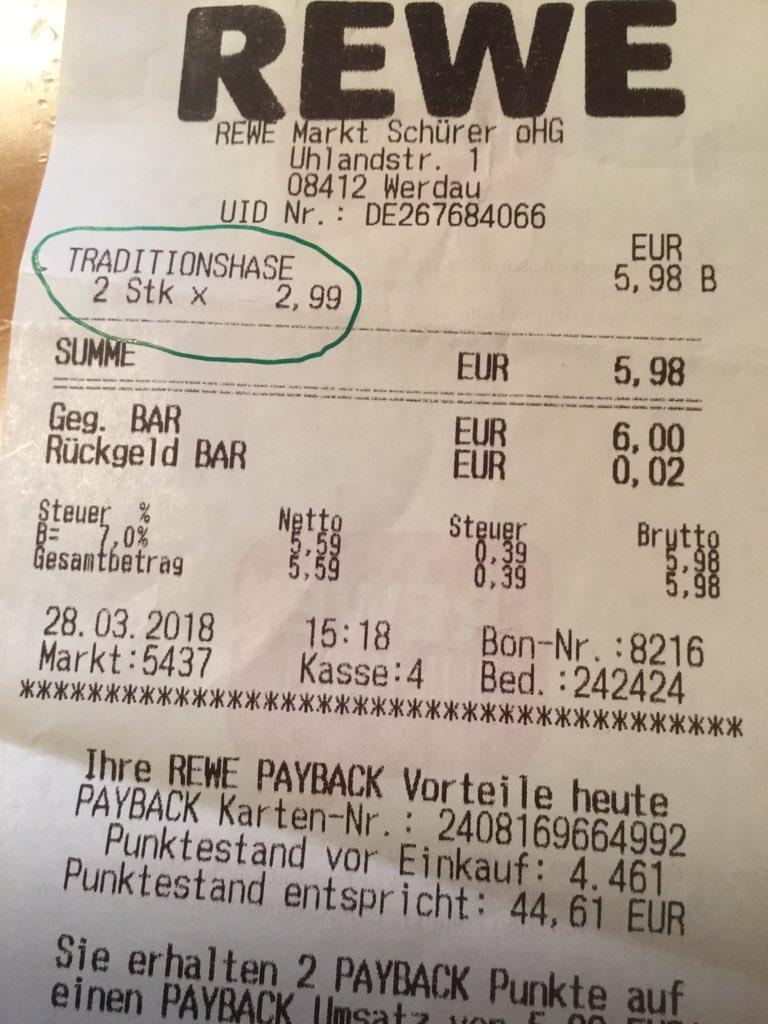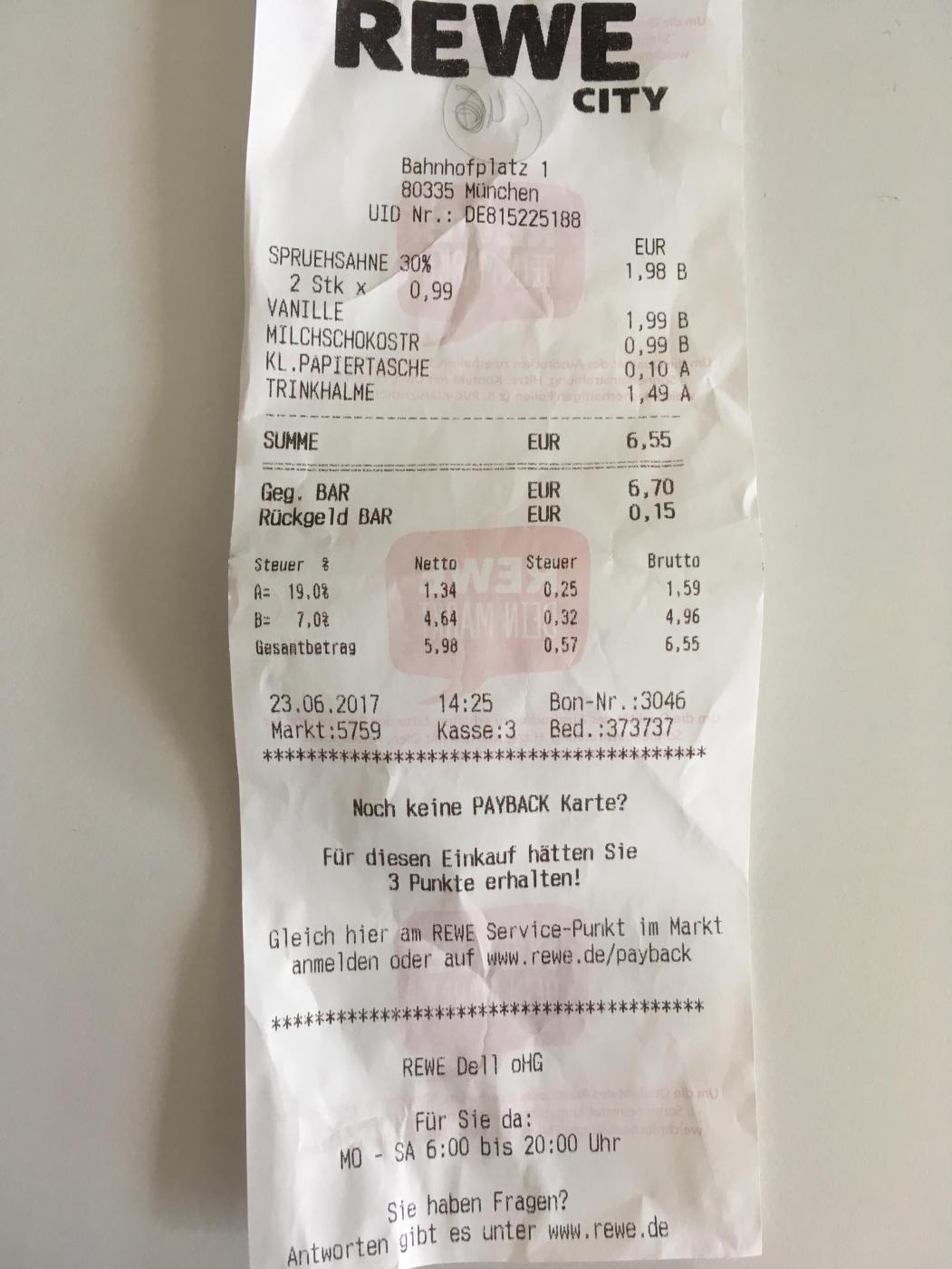
Rewe-Kassenbon-Schriftart
Ich bin auf der suche der Genuzten Schriftart der Rewe / Penny-Markt kassenbons.
Beide nutzen die selbe schrift art. Mit analyse programmen bin ich leider nicht sehr weit gekommen.
Wenn möglich suche ich eine Kostenlose alternative das die Orginale schriftart vermutlich nicht puplic ist , ist mir klar
eine alternative sollte so nah wie möglich an das orginal kommen.
Als kleiner extra hinweis es handelt sich nicht um eine Typische Pixelschrift diese wird bei Rewe seit jahren nicht mehr genuzt.
Das wurde hier schon diskutiert:
Ganz genau eben nicht , dort wird jedgliche art von kassen bons diskutiert da jede kette andere schriften nutzt und da keine einzige schriftart in diesem  über 1 Jahr alten Artikel nur annähernd dem orginal entspricht habe ich hier eine explizite frage nach REWE
Zusätzlich habe ich extra nochmal betont das ich keine pixel schriftart suche da dies seit über 1  jahrzehnt bei Kassenbons garnicht mehr genuzt wird
Die Schriftart hängt vom verwendeten Bondrucker ab. Da verschiedene Rewes verschiedene Kassensysteme verwenden, wäre eine Möglichkeit, auf dem Drucker nachzuschauen. Die Bezeichnung steht ja meist gut sichtbar drauf. Das führt dann über die Datenblätter zu den hardwaremäßig eingebauten Schriftarten.
Bei Epson-Druckern beispielsweise ist das "Schriftart A: 12 x 24" und "Schriftart B: 9 x 17", jeweils mit 2 Punkt-Zeichenabstand. Das Logo wird üblicherweise als bmp eingebunden, weil das keine Geschwindigkeitsnachteile beim Druck mit sich bringt.
Leider wieder falsch, das kassenstystem ist bundesweit bei allen Rewe märkten bei allen penny-märkten und bei allen Toom märkten gleich.
Es ist keine bondrucker schriftart, da Toom und Rewe zum beispiel verschiedene Drucker  nutzen die schriftart aber identisch ist.
Wie erklärst du dann, dass auf diesen zwei Rewe-Kassenbons unterschiedliche Schriftarten verwendet werden, wie man an den Zahlen leicht sehen kann?
Ah so. Das heißt, Rewe hat nach dem 23.6.17 bundesweit neue einheitliche Kassensysteme bekommen? Hab ich gar nicht mitbekommen …
Die alten Wincore Nixdorf TA 85 Kassensysteme werden seit anfag 2017 Bundesweit ausgetausch durch das neue Wincor-Nixdorf BA93 Touch  inklusive Kundenscanner für smartpones.
Wie du dir selbst anschauen kannst. Vereinzelt gibt es in deutschland private Märtke die bei der umstellung einspaarungen gemacht haben
wie zum beispiel , Altes kartenlesegerät ,oder alte drucker behalten. Dies ist aber sehr selten.
Und dann ist es auch bei den neuesten Kassensystemen nach wie vor eine Pixelschrift, bei den die Glyphen sogar, anders als bei alten PC-Pixelschriften sogar zeilenweise statt spaltenweise codiert. Der Drucker besteht nämlich aus einer Heizelement-Zeile, die über die Breite des Thermopapier-Streifens reicht, Jede der Glyphen-Zeilen werden bei den neuen Kassendruckern in 16Bit-Auflösung  im Zeichensatz-Rom gespeichert
Schaut man sich den Bon unter starker Vergrößerung an, sind die Pixel noch deutlich sichtbar.
Ich habe mal von einem Bon den ich grad habe das A ausgelesen, das schaut so aus:
Grafiken, wie das Laden-Logo am Bon-Kopf oder ein Angebot im Bon-Fuß werden in den Bondrucker als Schwarzweiß-GIF in genau der Druckerauflösung gespeichert.
Es macht nämlich überhaupt keinen Sinn, für Bon-Drucker Outline-Fonts zu verwenden, da ohnehin höchstens 2 Schriftgrößen in normal und fett verwendet werden. Wollen Firmen hier ihre eigene Schrift, gibt es eben die Pixelschrift zum Upload ins Zeichensatz-EEPROM.
Damals  musste das noch dann mit einem Programmiergerät in einen EPROM geschrieben werden, und dann der Bausteim im Gerät ersetzen.